Calli: ô Dề YC: đừng Cách điệu Hóa Font Chữ, Viết đúng Font Gốc Của ...
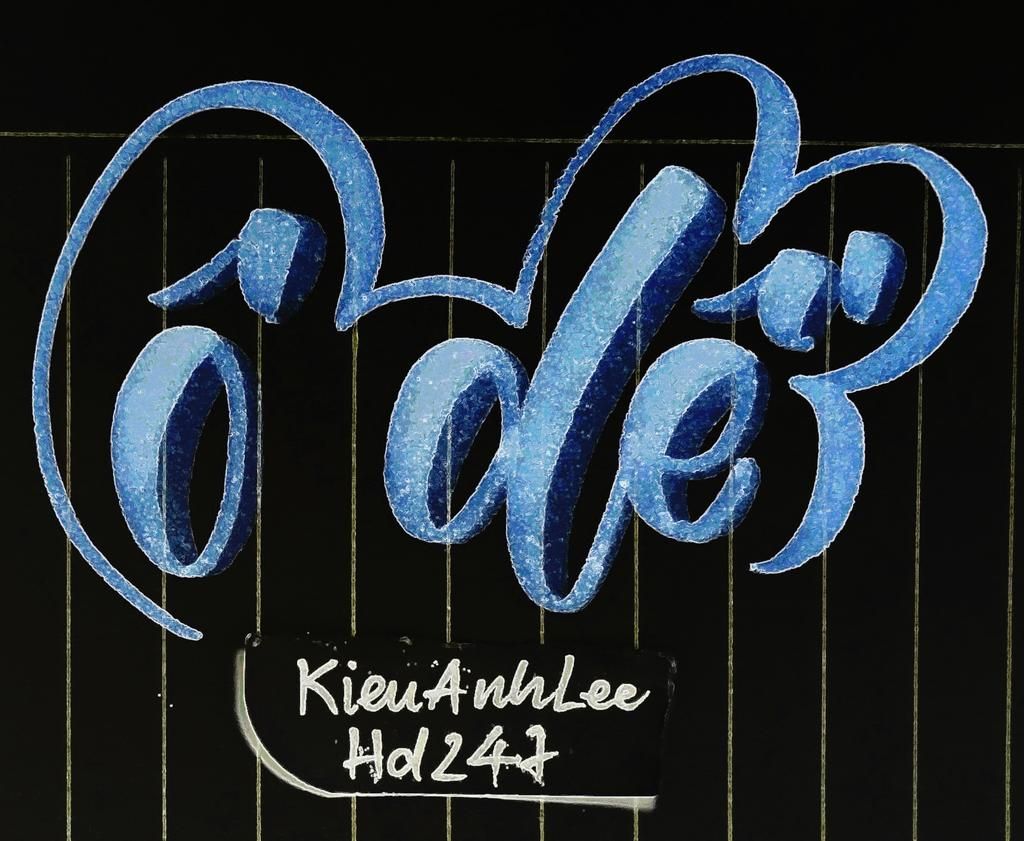
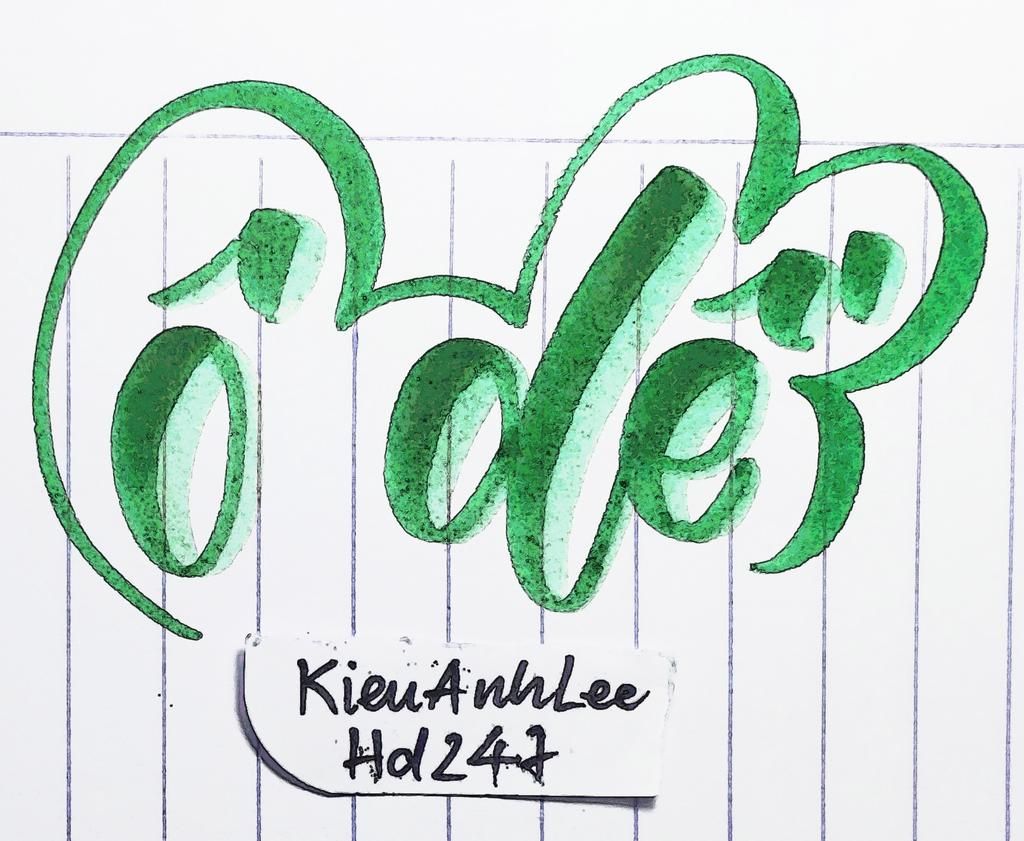
hnhu chữ ô k đúng lắm, theo e hc là khác chứ k chắc chắc đou ạ
Có font "o" như vậy mà cậu oi :|
ò, lúc trc mk vt ô nv r bị xóa ý :<